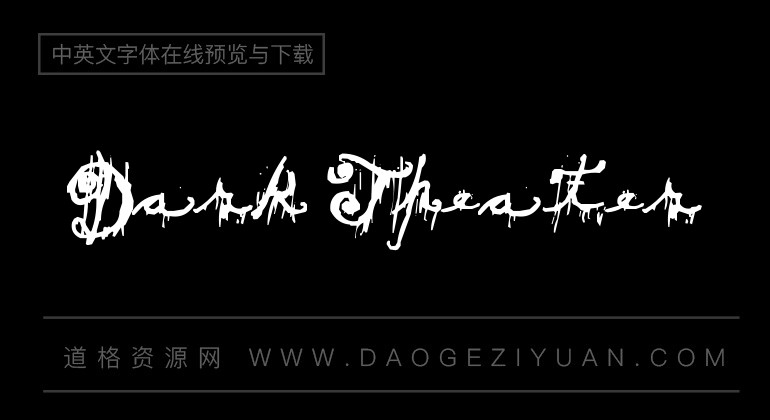
Dark Theater 字体是一款受到日本漫画影响的脏和暗的字体,它拥有独特的层次感和细节,可以提供出色的视觉效果。它的字体特点是深色的背景和黑色的字体,有着深沉的质感,更加突出了文字的形状,让文字更加凸显出来。它的字体结构也更加紧凑,可以更加细腻地表达文字的精细细节,让文字更加饱满有力。内容介绍
Dark Theater是一款非常不错的手写艺术字体,具有很好的视觉感,适合于文化类的宣传设计、商业类品牌的广告和产品包装设计以及个性化文字排版等较多场景。